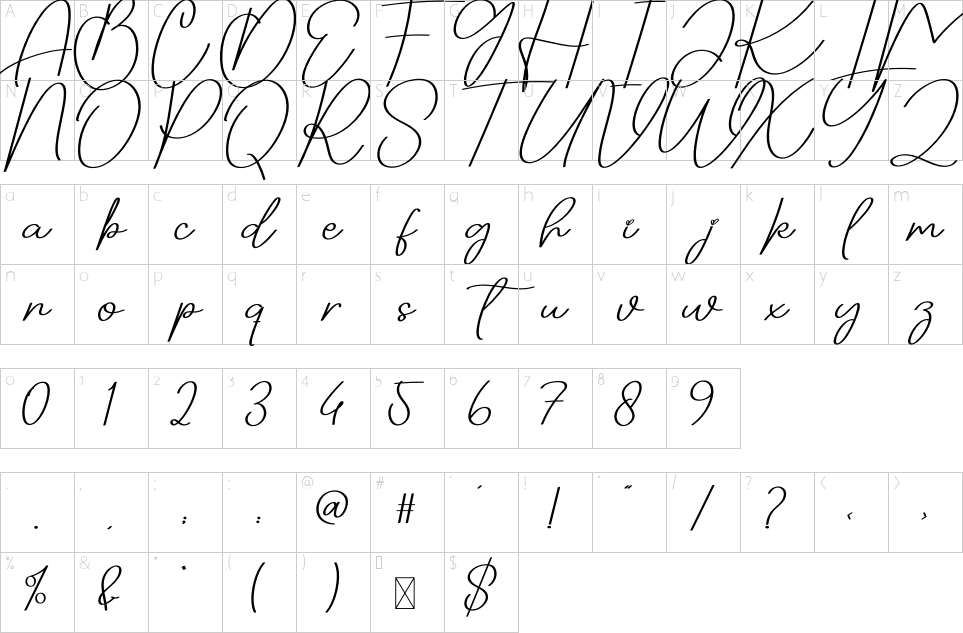
Aqui está uma descrição para a página de download da fonte ‘Destination Font’, seguindo as instruções fornecidas: ‘Sintaxe elegante e versátil, a fonte Destination é ideal para criadores de conteúdo que procuram um estilo clean para destacar seus textos. Desenvolvida pelo designer não informado scratchones, ela foi projetada para Windows e Mac. Com uma interface minimalista e sem afirmações exageradas, a fonte destaca-se como uma opção tranquila e confiável. Se você busca uma fonte simples mas poderosa, que se adapta perfeitamente ao seu trabalho de design, Destination é uma ótima escolha para sua coleção personalizada. Desde 397 downloads contabilizados, já provou sua eficácia no ambiente digital. Descubra como a ‘Destination Font’ pode reforçar o impacto visual de seus projetos.’